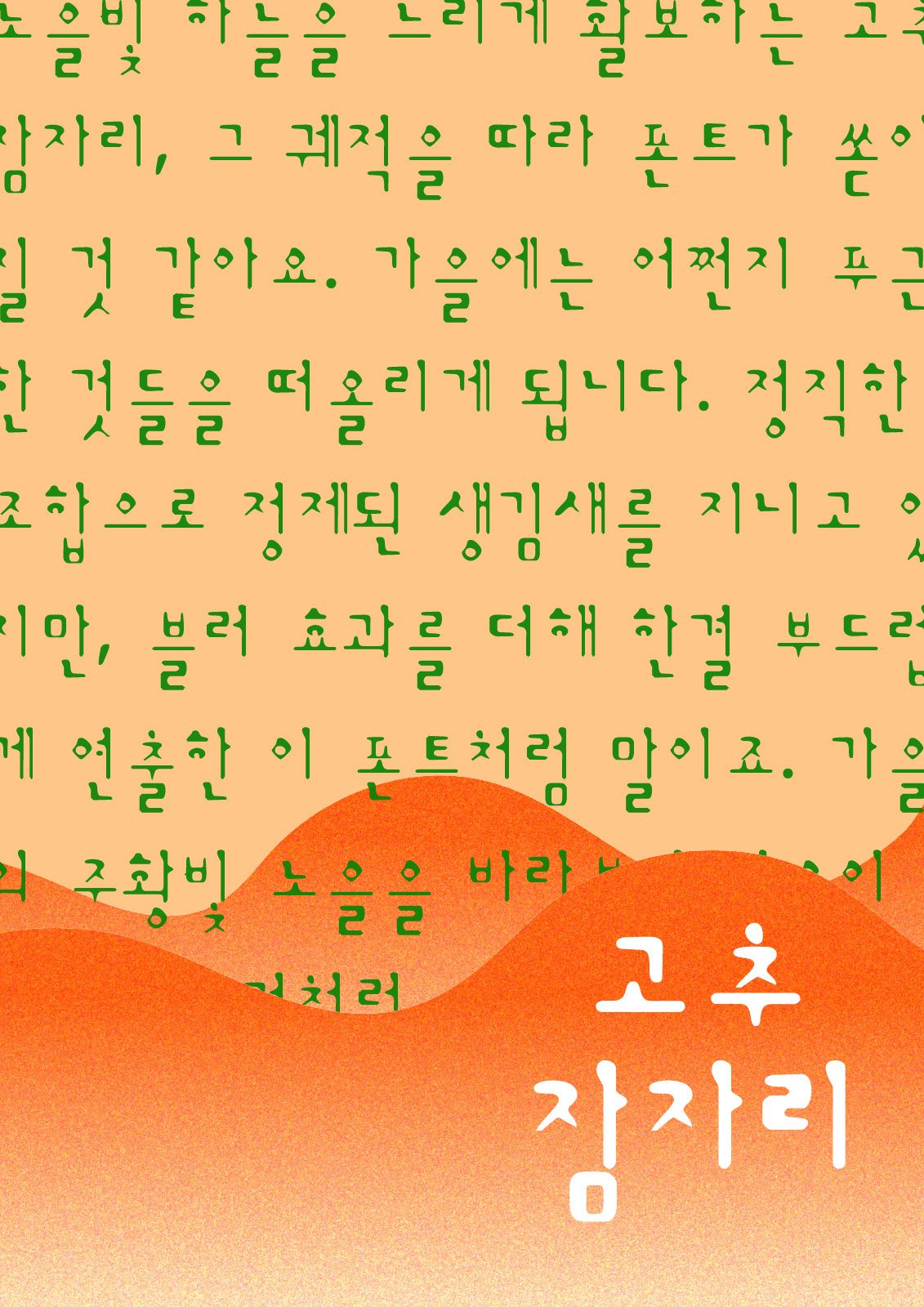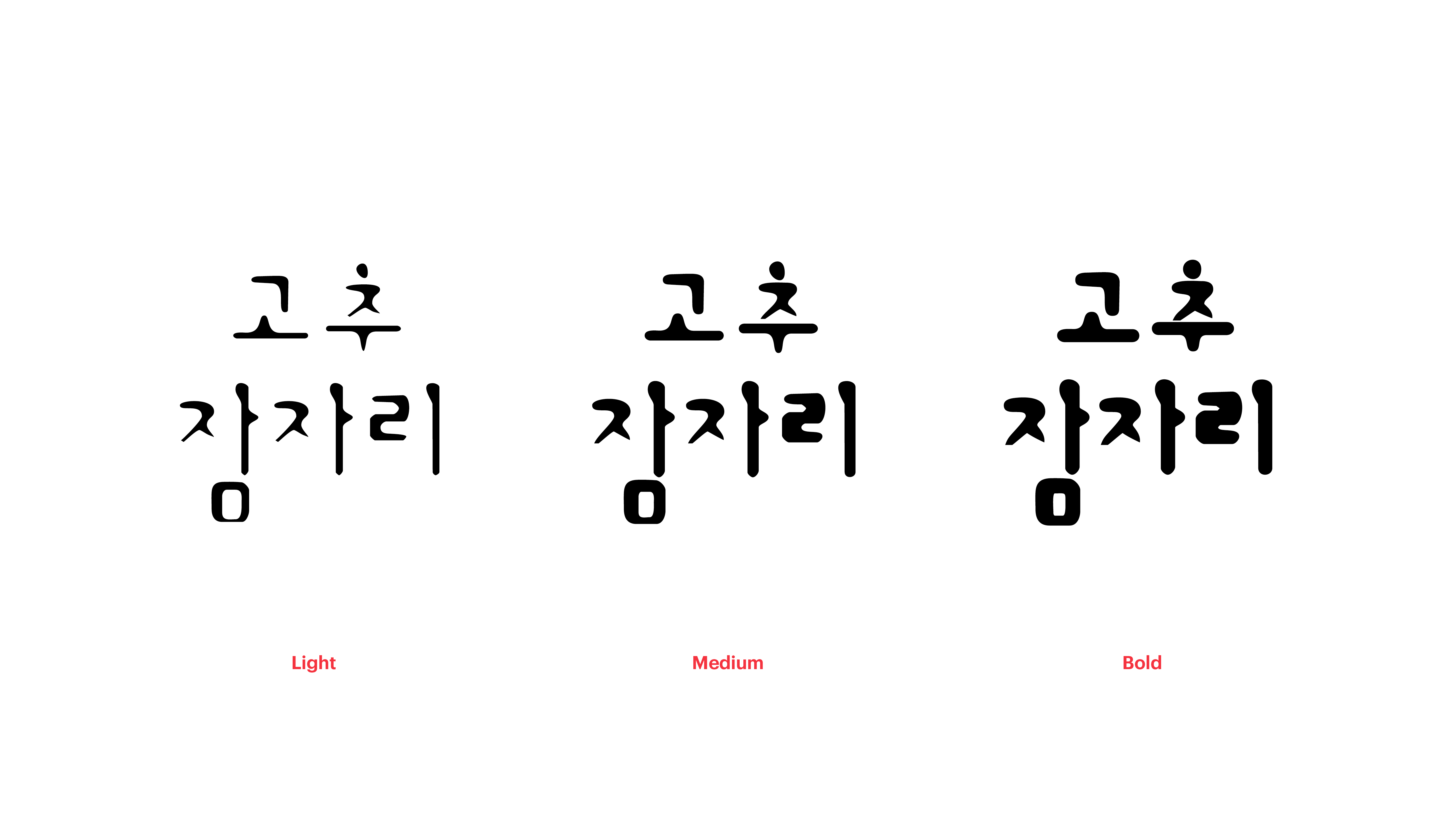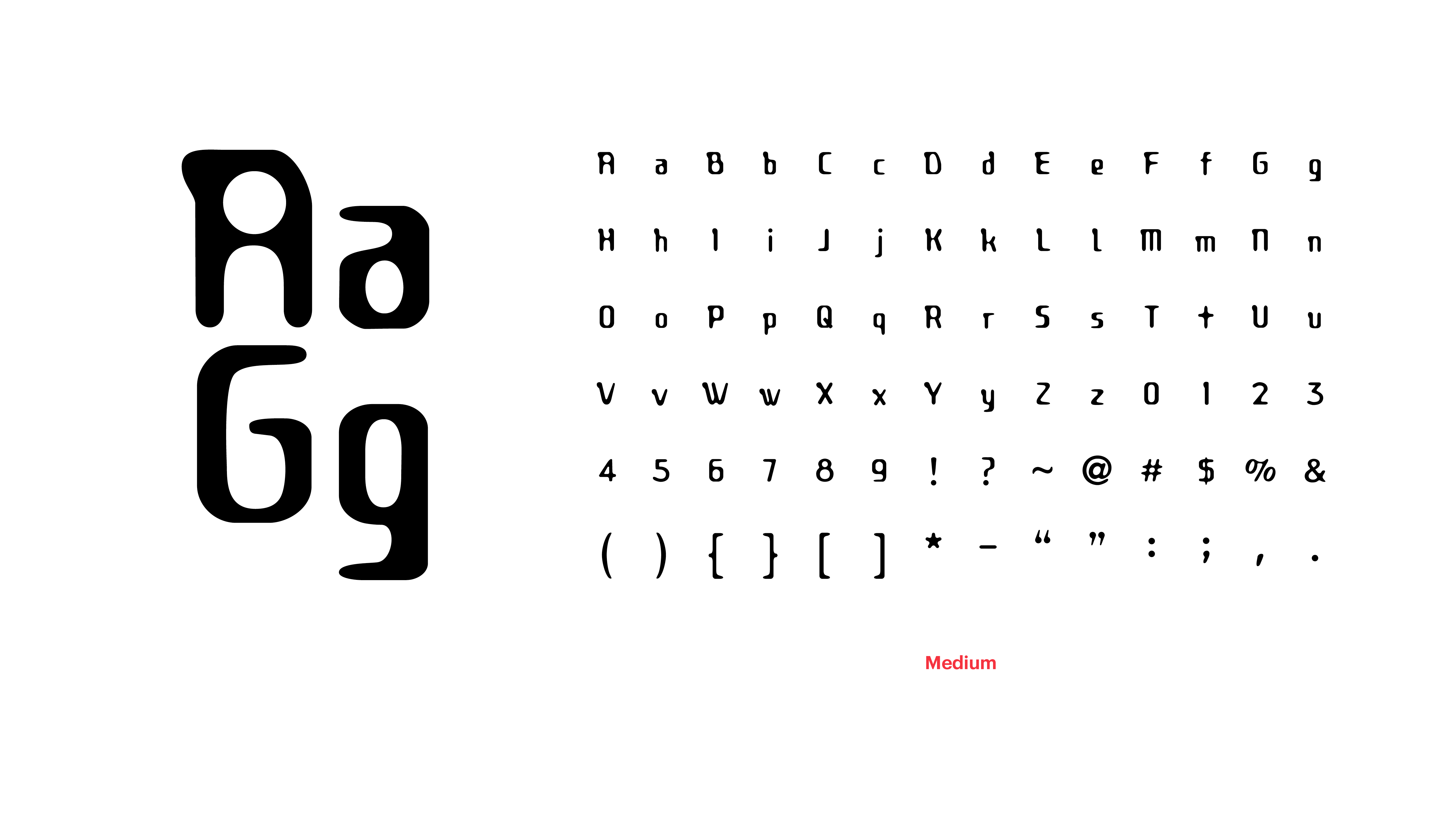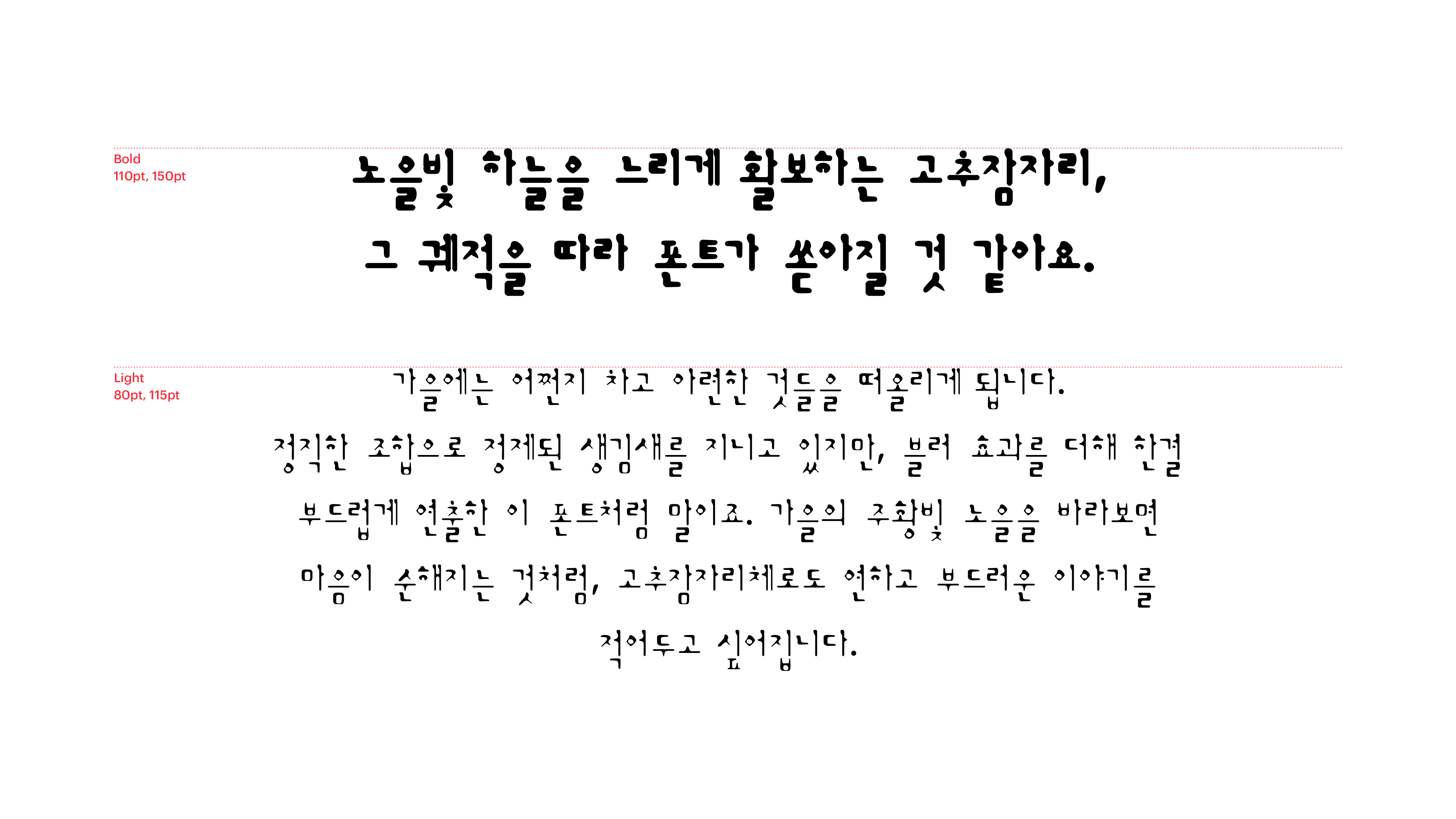
고추잠자리
Yoon 고추잠자리
가을에는 어쩐지 푸근한 것들을 떠올리게 됩니다. 정직한 조합으로 정제된 생김새를 지니고 있지만, 블러 효과를 더해 한결 부드럽게 연출한 이 폰트처럼 말이죠. 가을의 주황빛 노을을 바라보면 마음이 순해지는 것처럼, 고추잠자리체로도 연하고 부드러운 이야기를 적어두고 싶어집니다.